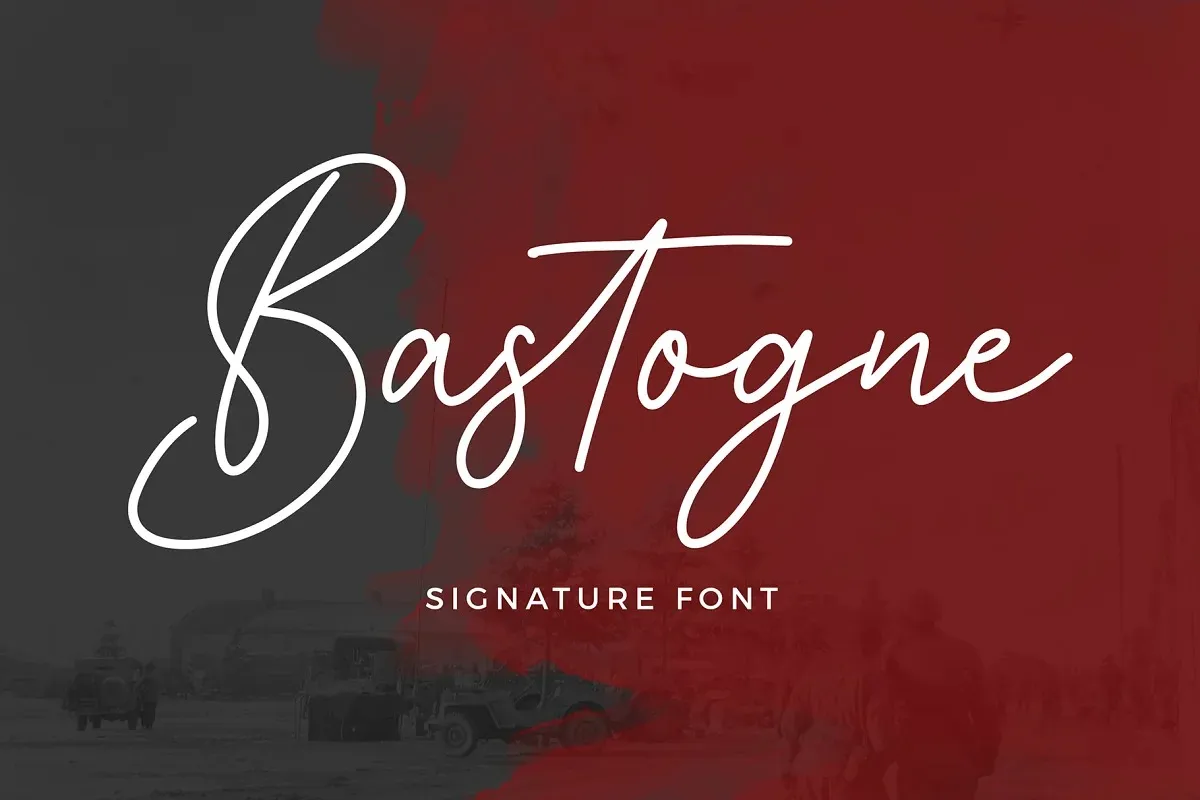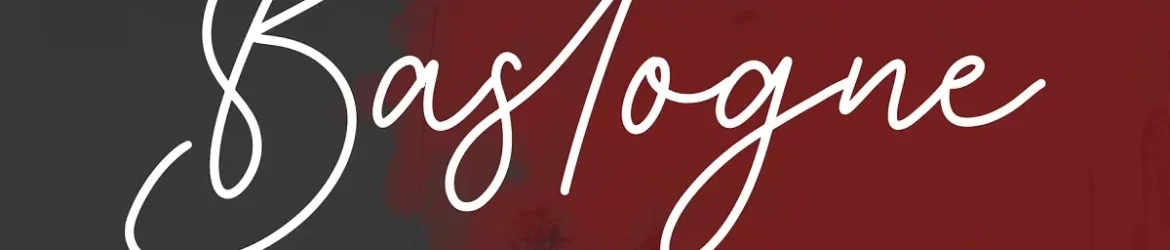
A fonte Bastogne é uma elegante escolha para projetos variados, não apenas pela sua aparência moderna e singular que evoca a beleza do hand-lettering, mas também por seu uso impecável nas mais diversas aplicações. Esta font é ideal para criação de marcas, logo, design para casamentos, posts nas redes sociais, anúncios, embalagens de produtos, designs de produto, etiquetas, fotografia e até mesmo como um marcador no filme ou em uma campanha de guerra clássica. O Bastogne traz ao seu trabalho uma autenticidade que não apenas fazça sua marca mais única, mas também oferece uma conexão emocional com seus clientes potenciais. Seja para um projeto de marketing digital, design gráfico ou até mesmo para o design de arte cinemática, a font Bastogne certamente fará toda a diferença.